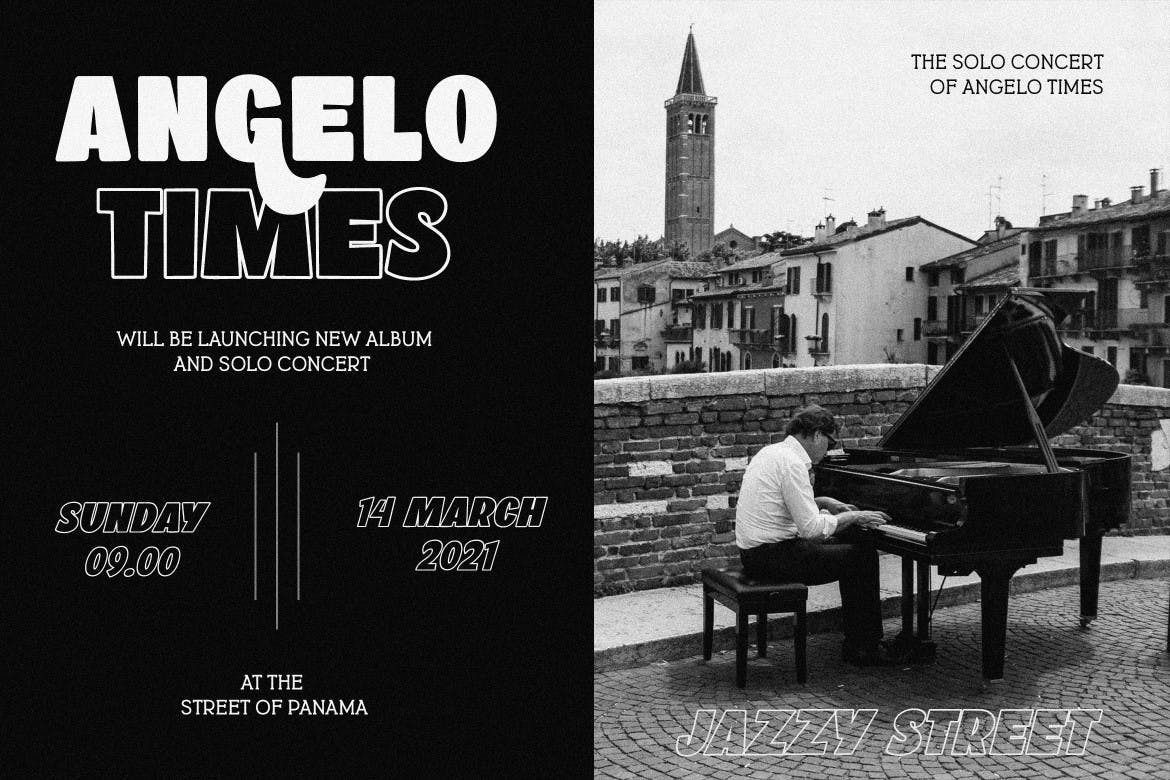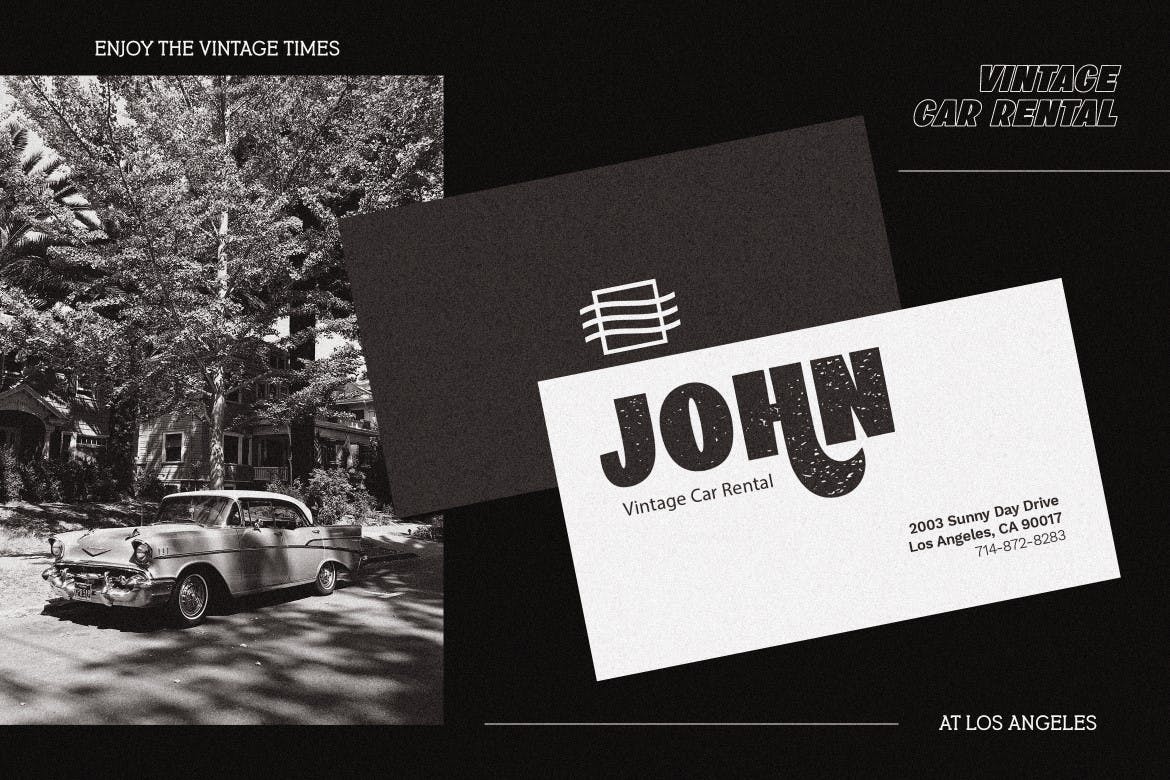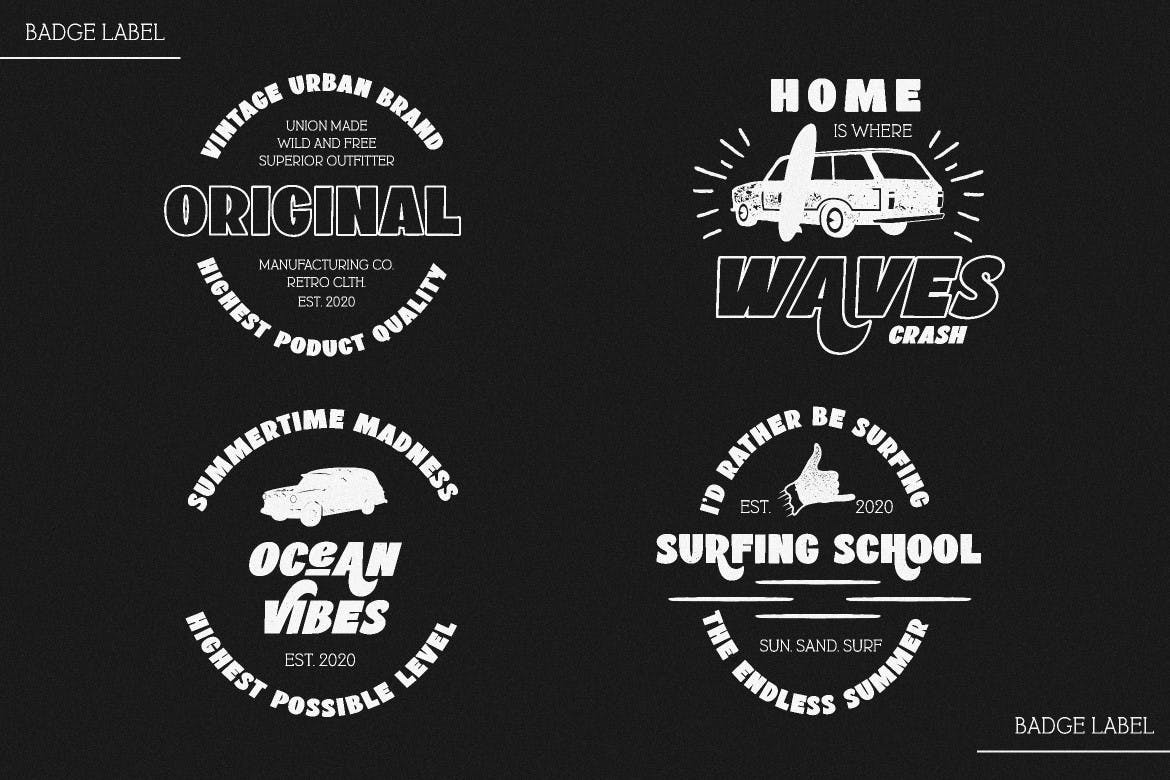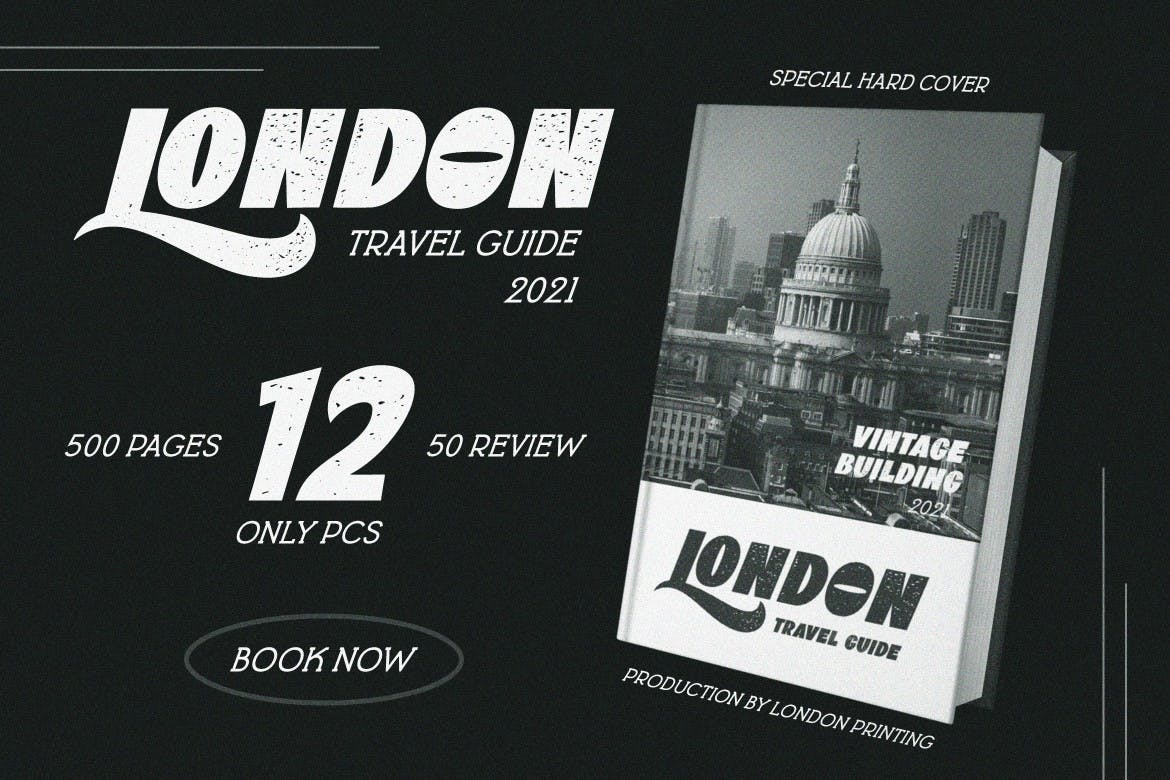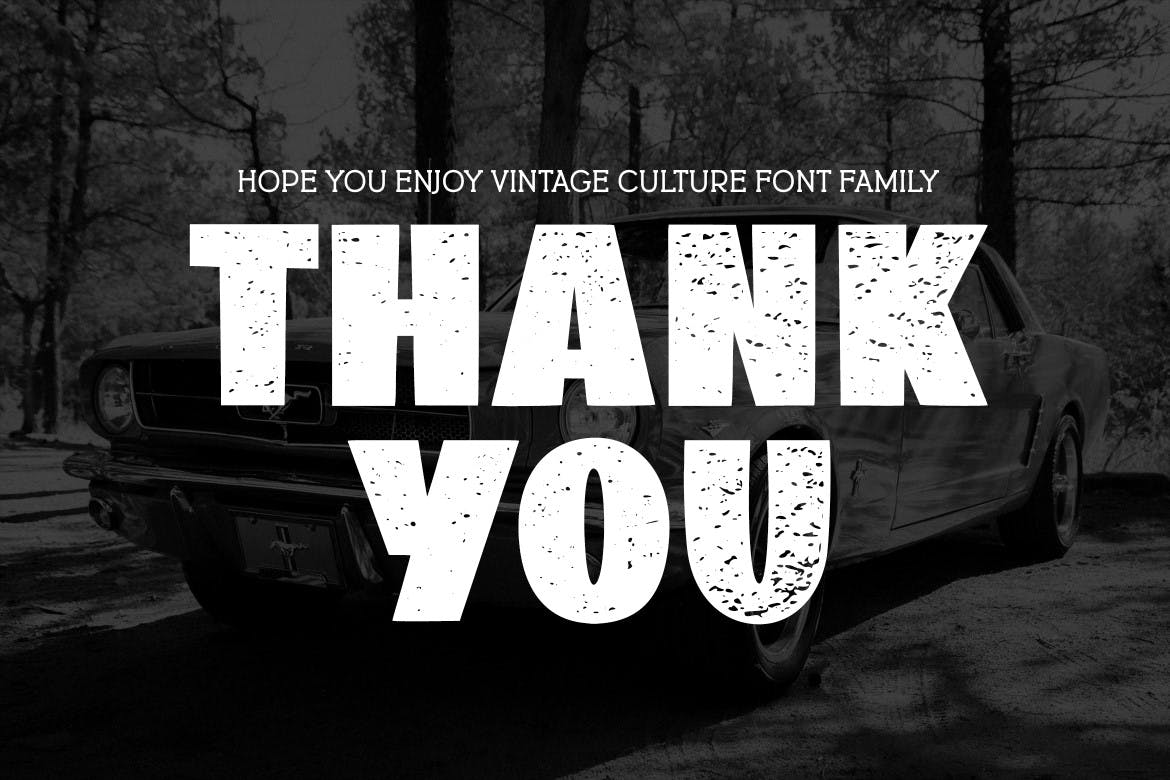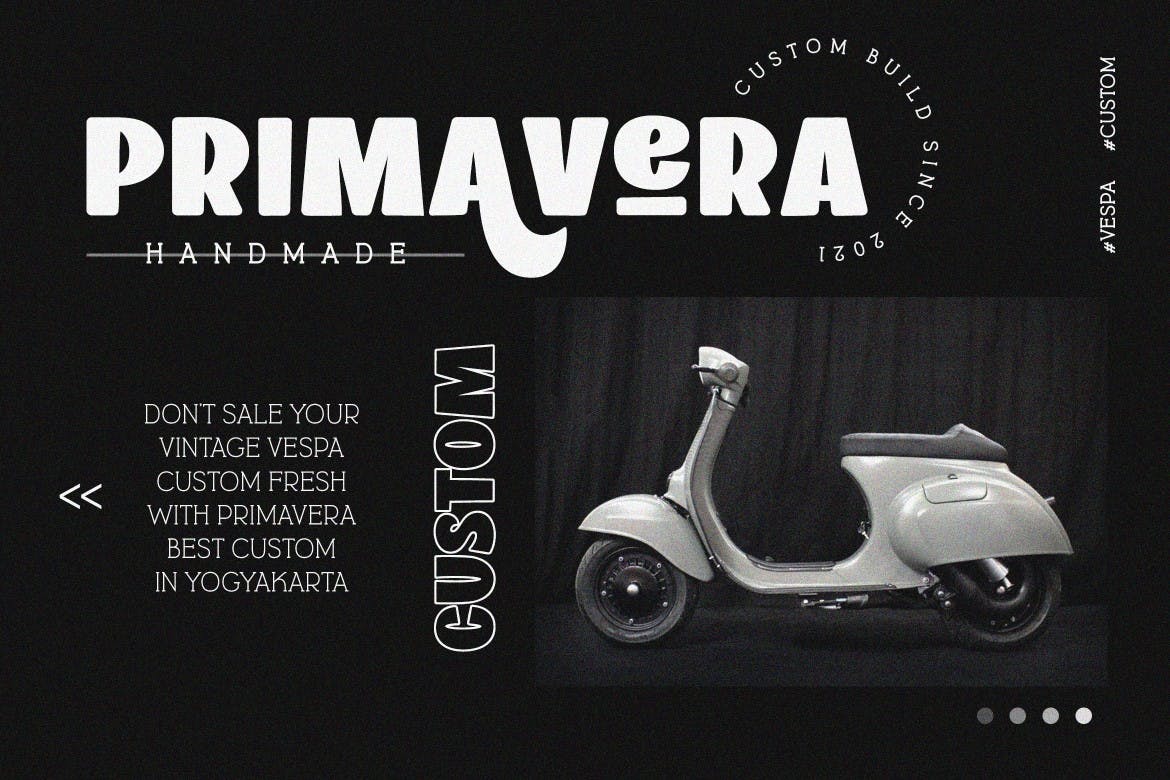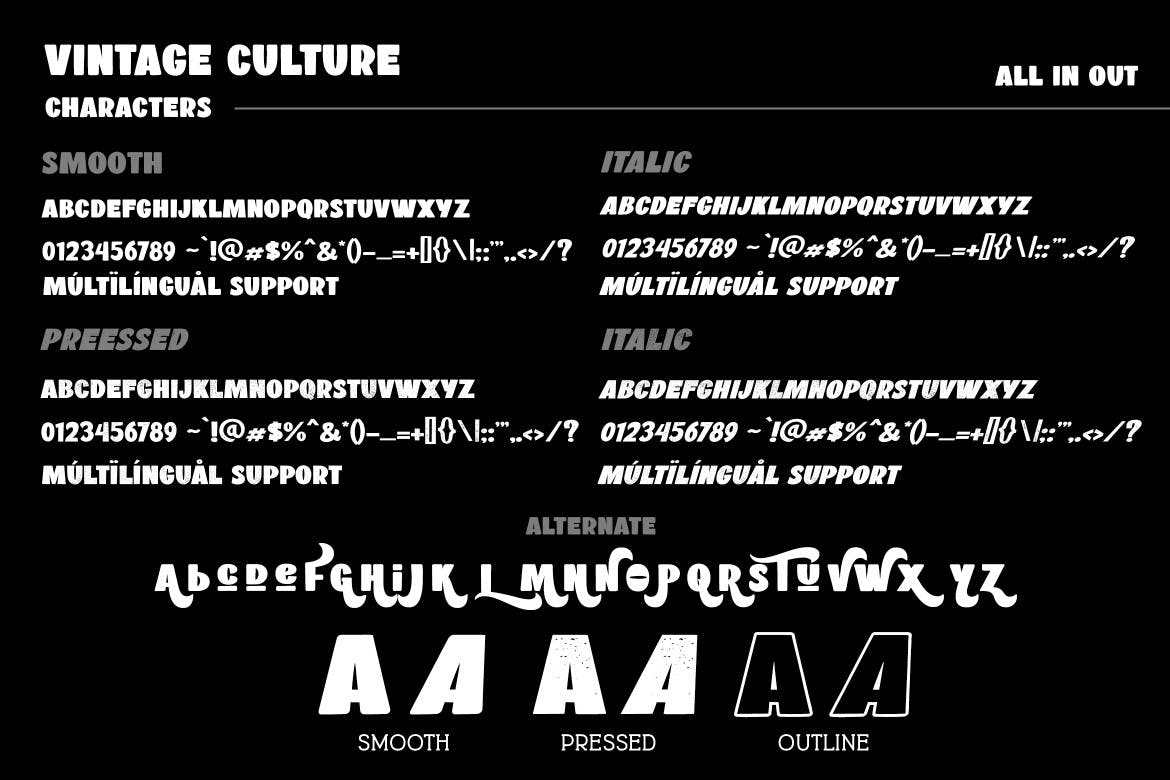
فونت Vintage Culture یک فونت ویژه برای طراحی لوگو و برندینگ شماست. هر کاراکتر این فونت به گونهای طراحی شده است که برای ساخت یک لوگوی جذاب مناسب باشد، بنابراین برای متنهای طولانی مناسب نیست.
شما میتوانید با استفاده از این فونت، لوگوی خود را به راحتی بسازید و از آن در وبسایت، چاپها، مجلات، پوسترها و پروژههای طراحی متنوع استفاده کنید.